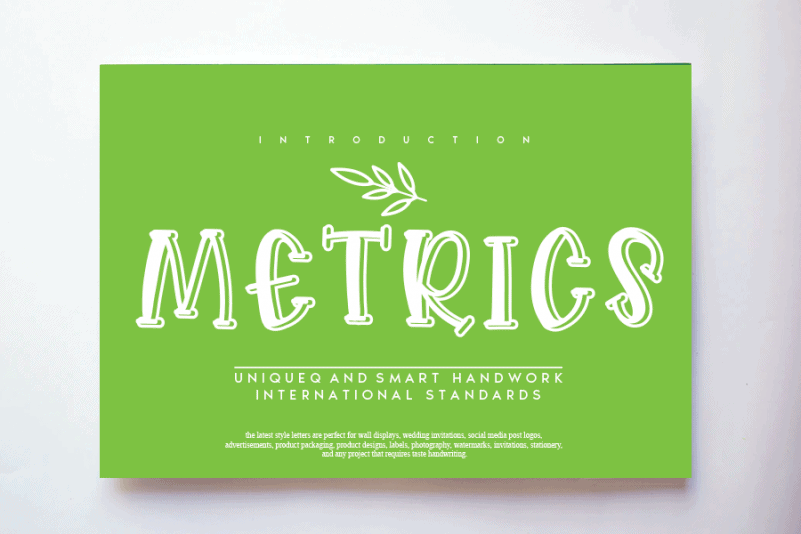
Metrics Display Font – Download Grátis
A Metrics Display Font é uma linda escolha para quem busca dar um toque especial às suas criações digitais. Com seus traços suaves e desenhos divertidos, essa fonte de exibição traz vida à sua marca ou projeto. Ela se destaca em cada detalhe do seu design, seja em nomes de produtos, slogans de marketing ou identidades visuais, tornando-os irresistivelmente atraentes. Adicione esta fonte elegante e única ao seu próximo projeto criativo e observe como ela torna seus conceitos se destacarem. Ideal para um toque personalizado e divertido que destaca sua marca no meio da multidão.